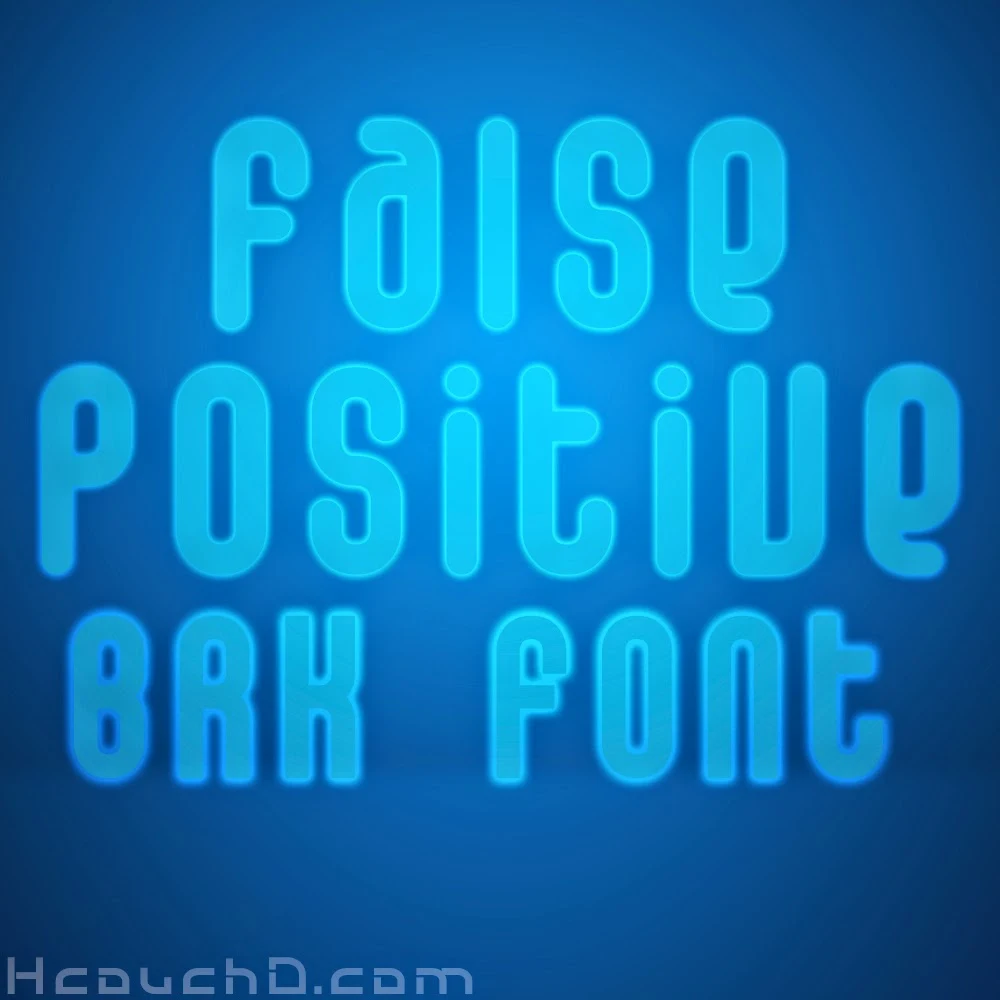
خط False Positive يعتبر من أفضل الخطوط ، و قوته في بساطته ، و يحتوي هذا الملف خطين الأول بحواف حادة و تاني بحواف دائرية ، يمكنك تحميل هذا خط من رابط أسفله …